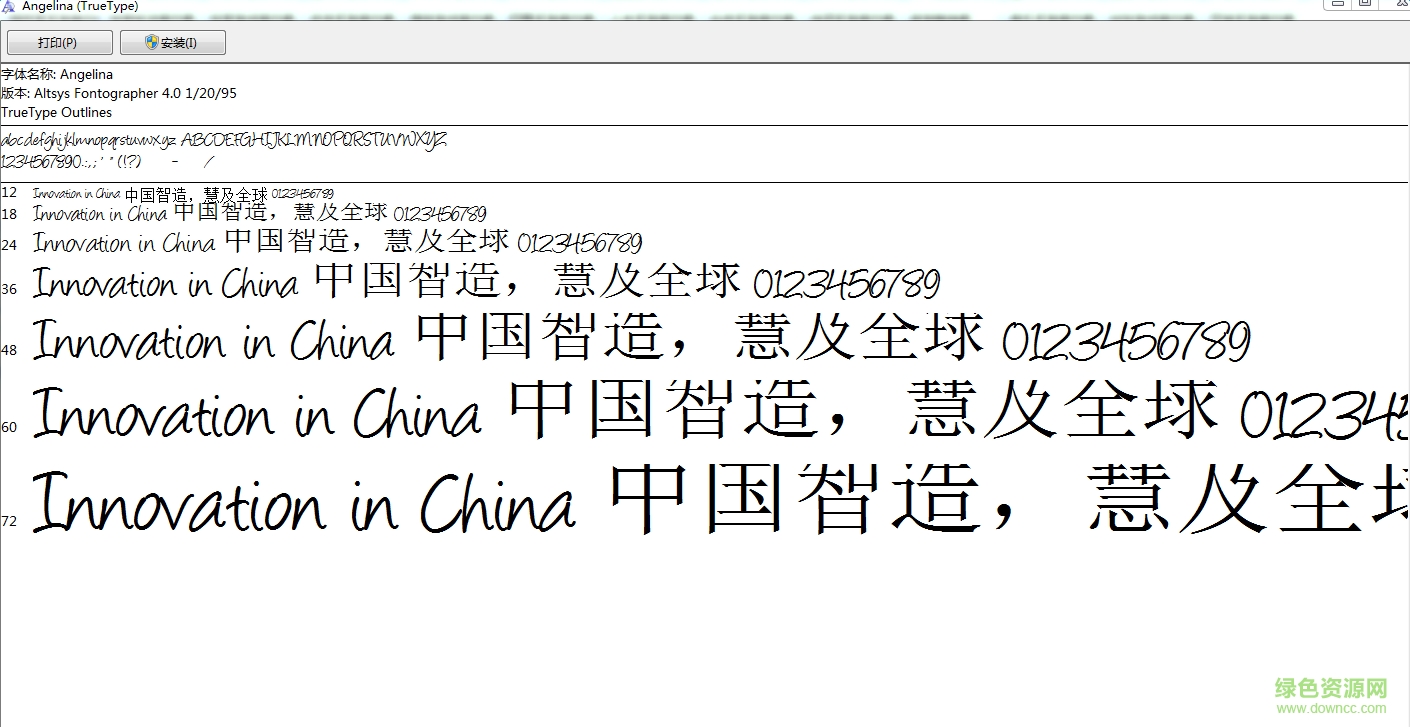
angelina字體是一款漂亮靈活的英文字體,線條隨意,結(jié)構(gòu)簡(jiǎn)單,非常具有生活氣息,用途十分廣泛,喜歡的小伙伴快來(lái)綠色資源網(wǎng)下載吧!
angelina是一款應(yīng)用于設(shè)計(jì)方面的字體,該字體線條粗細(xì)適中,英文飄逸有形,中文端正大方,能夠適用于產(chǎn)品包裝、廣告宣傳、出版印刷、商標(biāo)用字、商業(yè)網(wǎng)站、影視影像視頻、書籍出版印刷等,有需要的朋友可以免費(fèi)下載收藏。
該字體便利流暢,形神俱佳,效果出色,不論是用來(lái)做日常書寫用字還是廣告設(shè)計(jì)都非常合適!